Tải font chữ thời bao cấp là nhu cầu hàng đầu của các designer khi thực hiện các dự án thiết kế mang phong cách hoài cổ, tái hiện lại không gian văn hóa Việt Nam những năm 1970 – 1980. Với đặc trưng là những nét vẽ tay mộc mạc, thô sơ nhưng đầy tính nghệ thuật từ các bảng hiệu cũ, bộ font này mang lại diện mạo vô cùng độc đáo cho bao bì thực phẩm, quán cà phê và các ấn phẩm truyền thông Retro. Doozypack.vn chia sẻ link download font chữ thời bao cấp chuẩn, đã được Việt hóa chỉn chu để bạn tự do sáng tạo mà không lo lỗi hiển thị dấu tiếng Việt.
Đặc điểm thẩm mỹ độc đáo của phông chữ thời bao cấp
Để ứng dụng hiệu quả phong cách này, bạn cần hiểu rõ linh hồn của nó nằm ở sự không hoàn hảo một cách nghệ thuật của các nghệ nhân vẽ bảng biển xưa.
Nét vẽ tay thủ công và thô mộc
Đặc trưng lớn nhất của font chữ thời bao cấp là cấu trúc nét chữ mô phỏng lại áp lực của bút lông hoặc sơn xịt trên nền gỗ, tôn. Các đường nét thường có độ dày lớn, vững chãi nhưng các góc chữ lại hơi rung nhẹ hoặc không hoàn toàn thẳng tắp. Chính sự mộc mạc này tạo nên cảm giác gần gũi, chân thực, giúp thương hiệu của bạn kết nối mạnh mẽ với ký ức và cảm xúc của khách hàng.
Phong cách Typography đậm chất “Sài Gòn xưa” và Hà Nội cũ
Hệ thống phông chữ thời bao cấp thường bao gồm các dòng Sans-serif dày dặn hoặc các dòng Serif có chân bản lớn. Màu sắc đi kèm thường là các tông màu trầm, úa màu thời gian như vàng đất, đỏ đô, xanh rêu. Khi được sử dụng bản font chữ thời bao cấp Việt hóa free tại Doozypack.vn, hệ thống dấu thanh được thiết kế hài hòa, không đè nét, giữ nguyên được nhịp điệu Typography hoài cổ đặc trưng.
Tại sao designer nên sử dụng font chữ thời bao cấp Việt hóa cho thiết kế?
Trong ngành thiết kế đồ họa và sản xuất bao bì tại Việt Nam, phong cách Subsidy (bao cấp) đang trở thành một xu hướng bền vững:
- Xây dựng sự tin tưởng: Một chiếc hộp trà hay túi cà phê sử dụng font thời bao cấp gợi cảm giác về một sản phẩm có nguồn gốc lâu đời, uy tín và được làm thủ công tỉ mỉ.
- Giải quyết triệt để lỗi font: Các bộ font Retro nước ngoài thường bị lỗi ô vuông khi gõ tiếng Việt. Bản Việt hóa chuẩn từ Doozypack.vn giúp bạn gõ các slogan như “Cửa hàng bách hóa”, “Hương vị truyền thống” một cách trọn vẹn.
- Tạo dấu ấn độc bản: Giữa hàng loạt bao bì hiện đại tối giản, phong cách bao cấp giúp sản phẩm của bạn nổi bật hoàn toàn trên kệ hàng, thu hút sự tò mò của khách hàng ngay tức thì.
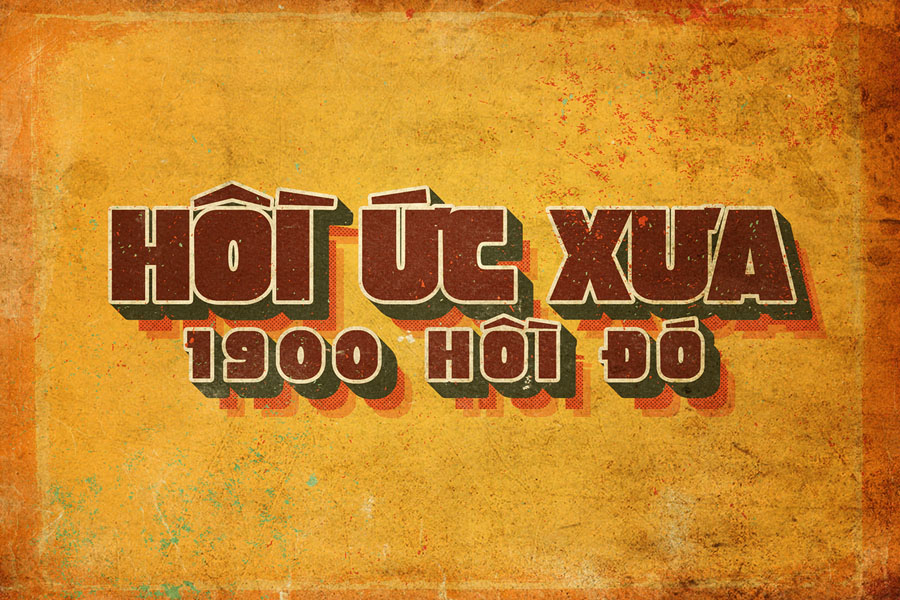
| Nhóm Font | Đặc điểm thị giác | Ứng dụng đề xuất tại Doozypack.vn |
| Font Bảng Hiệu (Signboard) | Nét dày, vững chãi, dứt khoát | Thiết kế tiêu đề hộp quà, biển hiệu quán cà phê, poster. |
| Font Brush (Bút lông) | Nghệ thuật, có độ xước tự nhiên | Dùng cho tiêu đề nhãn chai rượu, bao lì xì Tết, thiệp mời. |
| Font Retro Serif | Có chân cổ điển, trang trọng | Làm bảng thành phần, nội dung mô tả trên hộp trà, cafe. |
Ứng dụng của font thời bao cấp trong sản xuất bao bì tại Doozypack.vn
Vẻ đẹp vượt thời gian của nhóm font này mang lại hiệu quả thị giác đặc biệt trên các ấn phẩm thực tế do Doozypack.vn sản xuất:
- Hộp giấy đựng Cà phê & Trà: Kết hợp font bảng hiệu xưa với chất liệu giấy mỹ thuật nhám mang lại diện mạo đậm đà truyền thống và uy tín cho sản phẩm.
- Túi giấy shop thời trang Retro: Tên cửa hàng in bằng font chữ hoài cổ trên nền túi giấy Kraft nâu tạo phong cách Vintage hoàn hảo và thân thiện với môi trường.
- Tem nhãn đặc sản vùng miền: Rất phù hợp làm tên thương hiệu trên nhãn dán hũ mứt, tinh dầu hoặc thực phẩm đóng gói thủ công, tạo cảm giác an toàn và tự nhiên.
03 Lưu ý kỹ thuật khi in ấn phong cách Retro Việt Nam
Việc đưa một phông chữ có nhiều chi tiết thủ công lên chất liệu giấy đòi hỏi designer cần lưu ý một số vấn đề kỹ thuật tại xưởng in chuyên nghiệp:
- Hệ màu CMYK tông hoài niệm: Để có màu “retro” chuẩn, bạn nên phối màu dựa trên hệ CMYK với các tông vàng đất, đỏ đô hoặc nâu đen. Tránh sử dụng các màu quá tươi sẽ làm mất đi cái “hồn” của bộ font xưa.
- Lựa chọn chất liệu giấy: Font chữ thời bao cấp phát huy tối đa vẻ đẹp khi in trên các loại giấy có độ mộc như giấy Kraft, giấy Ivory cán màng mờ hoặc giấy mỹ thuật có gân nhám. Bề mặt giấy không bóng giúp nét chữ trông thật và có chiều sâu hơn.